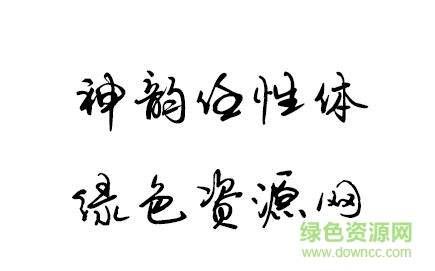
神韻任性體ttf字體是一款在使用的效果上能夠達(dá)到十分精美的顯示效果的字體,通過讓你在輸入以及使用的過程中獲得十分任性的體驗,讓你感受到暢快的視覺欣賞效果,快來綠色資源網(wǎng)下載吧!
這款字體的風(fēng)格非常不錯,在一眾神韻字體中能夠讓你獲得最佳的使用體驗,這款字體的特點在于字體風(fēng)光十分任性,快來體驗吧!